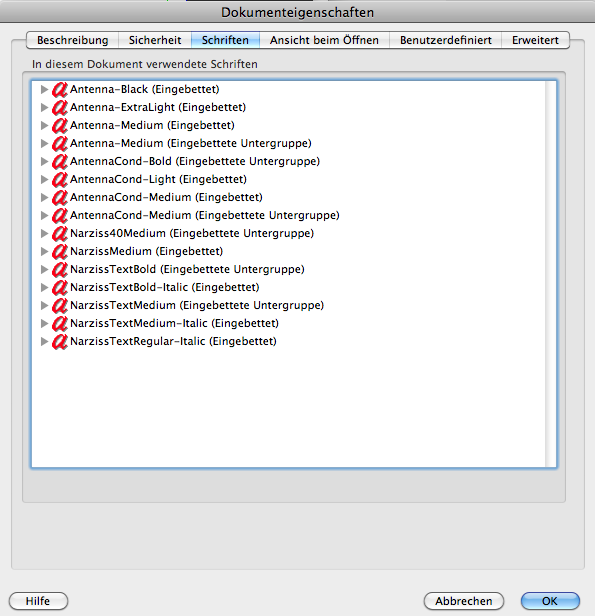
Zwei Schriften gesucht
ich suche schon eine Weile nach einer etwas eigenartigen Serifenschrift (Neue Headlineschrift der Zeitschrift FÜR SIE), bin aber noch nicht fündig geworden. Ich erinnere mich, dass hier im Forum vor kurzem schon einmal eine Schrift gesucht wurde, die ein ähnlich ungewöhnliches kleines »f« hatte. Auf der Suche danach bin ich zwar auf die EF Romana gestoßen, die passt aber ansonsten nicht zu meiner gesuchten Schrift. Hat einer von Euch vielleicht eine Idee, was das für eine Schrift ist? Und als zweites suche ich auch die serifenlose Subheadline-Schrift, aber die ist nicht ganz so wichtig.
Hier sind ein paar Fotos:
das ist ja super, vielen Dank – das ist sie! Das mit der Schräge beim J kommt nur durch die Wölbung der Vorlage zustande. Ich hatte gestern keinen Scanner zur Hand und habe die Schriften aus der aufgeschlagenen Zeitschrift abfotografiert.
Ein Vorschau-pdf der aktuellen Ausgabe verrät mir: